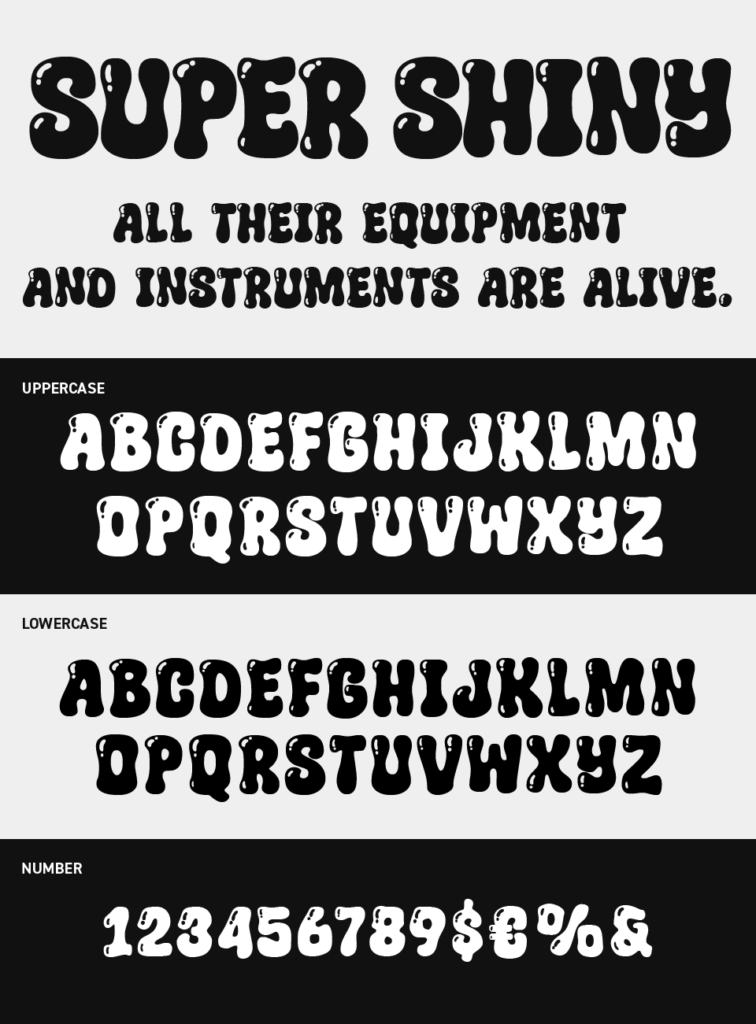
Super Shinyフォントは、ぷっくりとした立体感とツヤのあるハイライト表現が特徴的なバブル系なデザインフォントです。
インクがとろけるような質感があり、文字そのものがキャラクターのように感じられるユニークなフォントです。
手書きっぽいやわらかさがありつつポップなどで、カラフルな配色とも相性が良く、楽しく弾けるような空気をまとい、インパクトある見出しなどにしたい場面にぴったりなフォントです。
収録文字は、大文字/数字/記号の収録となっています。